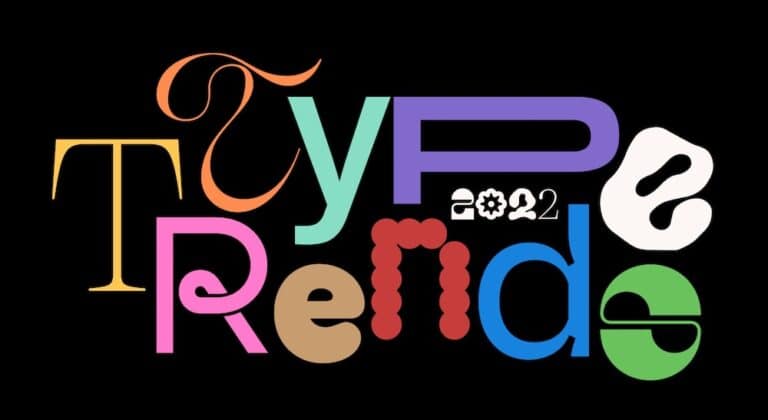
Type Trends 2022
Monotype veröffentlicht einen Report, in dem das Unternehmen zehn Typotrends für dieses Jahr identifiziert.
In seinem Type Trends Report fasst der Anbieter von Schrift und -Technologie die wichtigsten Entwicklungen im Bereich Design und Gestaltung zusammen. »In diesem Jahr haben wir erstmals versucht, die Trends mit den Entwicklungen zu synchronisieren, die uns bewegen, also: Umwelt, Pandemie, die Verlangsamung der Zeit, die rapide Akzeptanz alles Digitalen, die sozialen Medien als Treiber des sozialen Wandels, Nostalgie, das Hinterfragen von Fakten, Diversität versus Zusammenhalt und natürlich die Sorge um das eigene Ich«, sagt Charles Nix, Creative Type Director bei Monotype. »Das Ergebnis ist eine Hommage an die gesamte Schriftbranche, ein Wirtschaftszweig, der unsere Kultur widerspiegelt und vorantreibt.«
Die wichtigsten Trends sind:
NF-Type: Der Trend korrespondiert mit dem Thema »Design für Metaverse«. NFTs und jetzt NF-Type sorgen gerade für viel Gesprächsstoff und es wird darüber diskutiert, wie wir das Lizenzieren von Schriften und deren Vertrieb auf einem dezentralen Markt erneuern können. Die Animation Weird Whales des 12-Jährigen @ObiWanBenoni, Brikfont von Craig Ward und die Font DOT Community zeigen, wie stark diese Kategorie im Kommen ist.
Weird Whales. Agency/designer: Obiwanbenobi via OpenSea.
NFTYPE. Agency/designer: NFTXYZ.
Brikfont. Agency/designer: Craig Ward.
Grazile Serifen: Feine, schlanke Serifen sind wieder in. Der Trend »Schlanker Fuß« ist ein raffiniertes Update des Weichzeichner-Trends aus dem letzten Jahr, als fette, kurvige Serifen groß in Mode waren. Die Kooperation der US-Agentur Collins mit dem Schweizer Schriftenhaus Dinamo für das Branding der San Francisco Symphony ist ein schönes Beispiel für die Umsetzung dieses Trends.
SF Symphony. Agency/designer: Collins.
Half Full. Agency/designer: Inside Fred.
Mix-up: Influencer, Communities und die Kultur insgesamt haben sich Vielfalt, Fluidität, Mehrdeutigkeit und Integration auf die Fahnen geschrieben. Stilmix ist typografische Vielfalt, die mehrere Schriftstile zu einer Identität vereint, um Diversität in Gemeinsamkeit zu überführen. Die Gestaltung des Buchs »Innovation by Design« (Herausgeber: Fast Company; Agentur: Triboro) und die neue Markenidentität von Henkel (Agentur: Interbrand, DE) sind nur zwei Beispiele dafür, dass es unsere Unterschiede sind, die uns ausmachen.
Henkel. Agency/designer: Interbrand.
Gotong Royong (Communal Work). Agency/designer: Huruf type collective.
Flux: Während du schliefst, wurde alles lebendig. Bücher begannen zu sprechen. Gerahmte Bilder begannen, sich zu bewegen und zu verändern. Plakate wurden zu animierten 2-D-Flächen. Bei Im Fluss ist die Schrift hyperkinetisch, manchmal animiert, manchmal variabel, immer in Bewegung. Die Agenturen Studio Dumbar und Robu, sowie das Branding für MIDI von Pentagram tragen zu diesem siebenteiligen Trend bei.
MIDI. Agency/designer: Pentagram.
Focus. Agency/designer: Simon Eves.